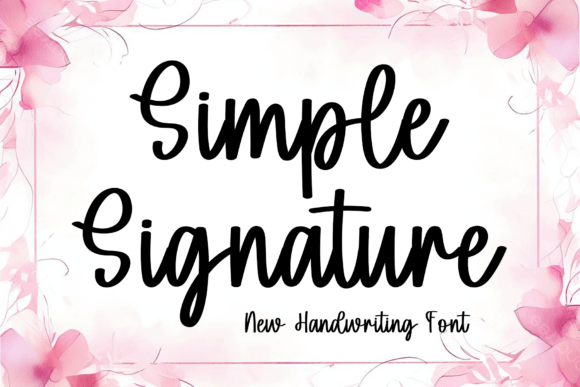
Simple Signature
์˜ฌ๋ฐ”๋ฅธ ๋””์ž์ธ ์š”์†Œ๋ฅผ ์ฐพ๋Š” ๊ฒƒ์€ ์–ด๋ ค์šธ ์ˆ˜ ์žˆ์ง€๋งŒ Simple Signature๋Š” ์ž‘์—…์„ ์ฆ‰์‹œ ํ–ฅ์ƒ์‹œํ‚ค๋Š” ๋›ฐ์–ด๋‚œ ์ปฌ๋ ‰์…˜์„ ์ œ๊ณตํ•ฉ๋‹ˆ๋‹ค.
์ •๋ฐ€ํ•˜๊ฒŒ ์ œ์ž‘๋œ Simple Signature๋Š” ๊น”๋”ํ•œ ๋ฒกํ„ฐ, ๋ถ€๋“œ๋Ÿฌ์šด ํƒ€์ดํฌ๊ทธ๋ž˜ํ”ผ ๋ฐ ์•ˆ์‹ฌํ•  ์ˆ˜ ์žˆ๋Š” ์ƒ์—…์šฉ ๋ผ์ด์„ ์Šค๋ฅผ ์ œ๊ณตํ•ฉ๋‹ˆ๋‹ค.
POD(์ฃผ๋ฌธํ˜• ์ธ์‡„) ์ œํ’ˆ, ๊ฒฐํ˜ผ์‹ ์ดˆ๋Œ€์žฅ ๋˜๋Š” ์†Œ์…œ ๋ฏธ๋””์–ด ๊ทธ๋ž˜ํ”ฝ์„ ๋งŒ๋“ค ๋•Œ Simple Signature๋Š” ์ด์ƒ์ ์ธ ์„ ํƒ์ž…๋‹ˆ๋‹ค.